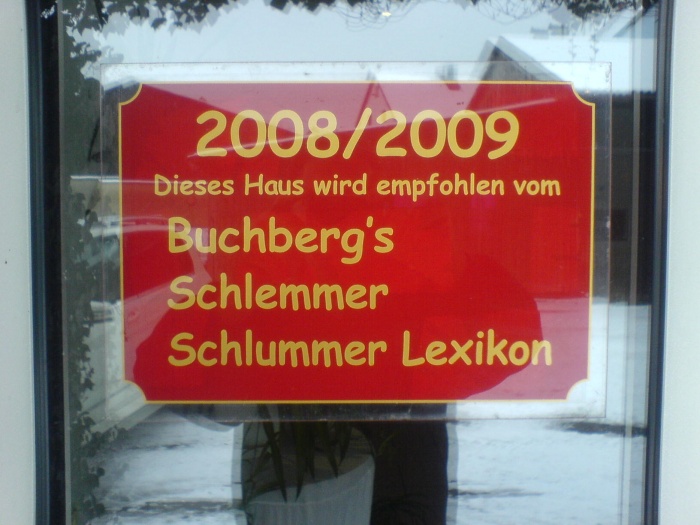
Typografie und Seriosität
gestern waren wir in einem Restaurant im Landkreis Kelheim / Bayern.
An der Eingangstüre prangte ein Schild, siehe das angehängte Bild. Ich ahnte, das sollte wohl so eine Art Qualitätssiegel sein.
Was mir als Amateur-Grafiker und Typografie-Laie sofort negativ auffiel, von der verschmutzen Laminierfolie einmal abgesehen, war die verwendete Schrift "Comic Sans".
Eben googelte ich mir noch die Webseite www.hotel-restaurant-verzeichnis.de
Dort wird im Header die Papyrus verwendet.
Seriosität, selbst wenn sie nur unterschwellig wahrgenommen wird, kann man sicher nicht mit so einer Schriftart und einem solchen Design erzeugen. Mit solchen Schildern kann man sicher der Landbevölkerung die dort einkehrt imponieren, aber sonst niemandem.
Einfach nur grausam, aber für mich ein schönes Lehrstück, wie man es NICHT macht.
auf sowas gebe ich eh nix, heutzutag kann sich ja jeder eine seite hochziehen und dort dann nach irgendwelchen kriterien restaurants bewerten.
die gestaltung zeigt dann sicherlich auch den stellenwert dieses 'lexikons'.
Naja, zur ComicSans und der Papyrus ist ja in unzähligen Beiträgen schon viel gesagt.
Mich stört vielmehr der schludrige Sprachgebrauch: eine Datenbank, ein Restaurantverzeichnis ist nunmal kein Lexikon. Und der Umbruch ohne Kopplungen lässt mich rätseln, ob Buchberg Schlemmer und/oder Schlummer und/oder Lexikon ist. Vom Genitiv-Apostroph und dem zweifelhaften Dativ will man da dann auch nimmer reden.
„… Mit solchen Schildern kann man sicher der Landbevölkerung die dort einkehrt imponieren, aber sonst sicher niemandem …“
Dass man der Landbevölkerung „sicher“ damit imponieren kann, bezweifle ich.
Wie kommst du darauf?